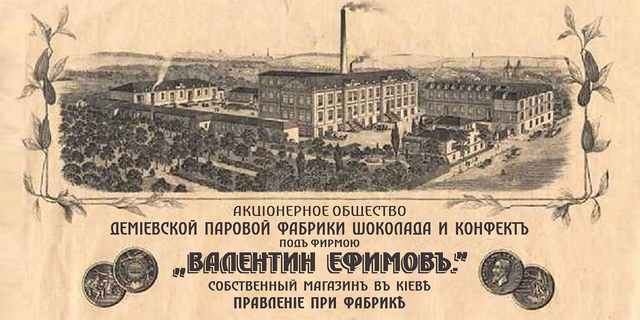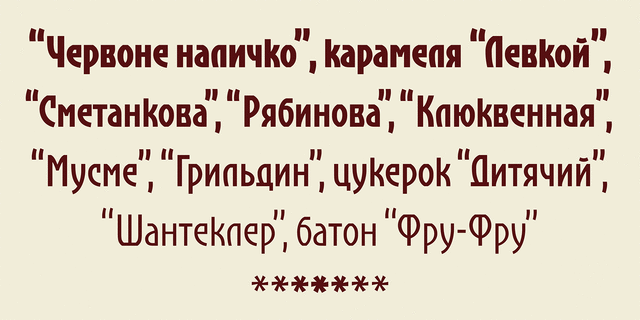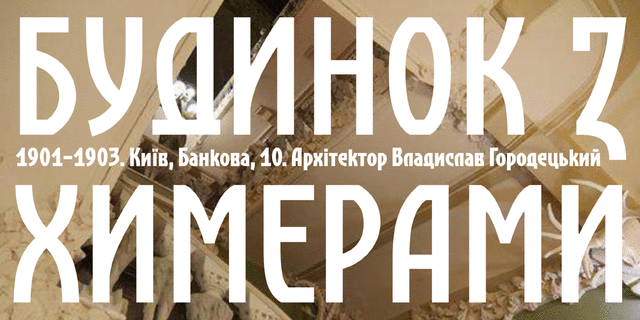
Основой этого шрифта стала реклама Киевской кондитерской фабрики. Затем шрифт был расширен до шрифтовой гарнитуры, что значительно увеличило возможности использования. Стилистически шрифт несет все признаки гротеска в стиле Модерн – сдвинутые вверх и вниз оптические оси, искривленные дуги и прямые штрихи, капризные и неожиданные решения отдельных букв. В то же время некоторая геометризированность позволяет ему уверенно держать строку, а суженные пропорции и светлые начертание прекрасно подходят для составления небольших надписей в рекламе, вывесках, журналах, меню, упаковке и т.п. Шрифт разработали Геннадий Заречнюк и Виктор Харик в 2019–2020 годах.